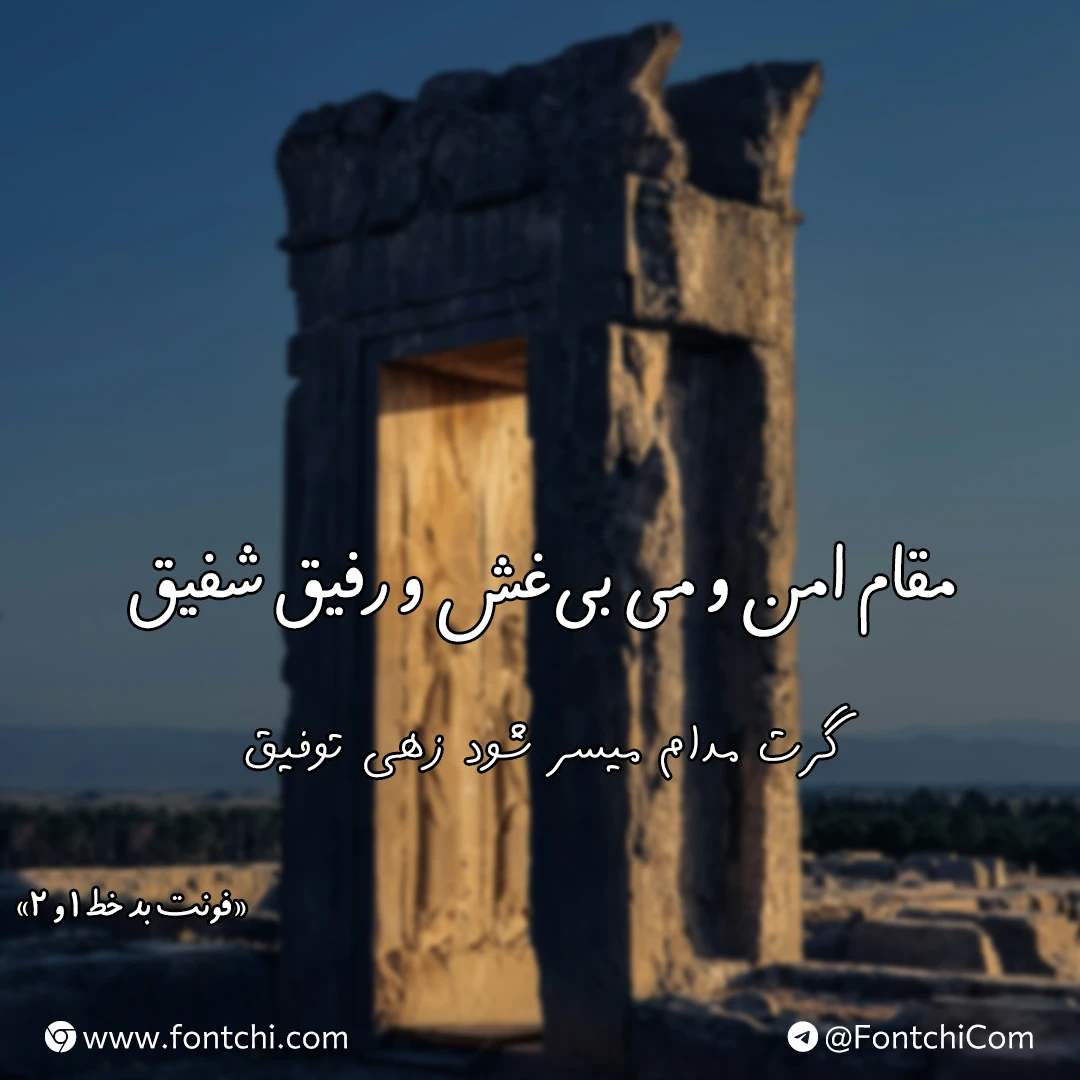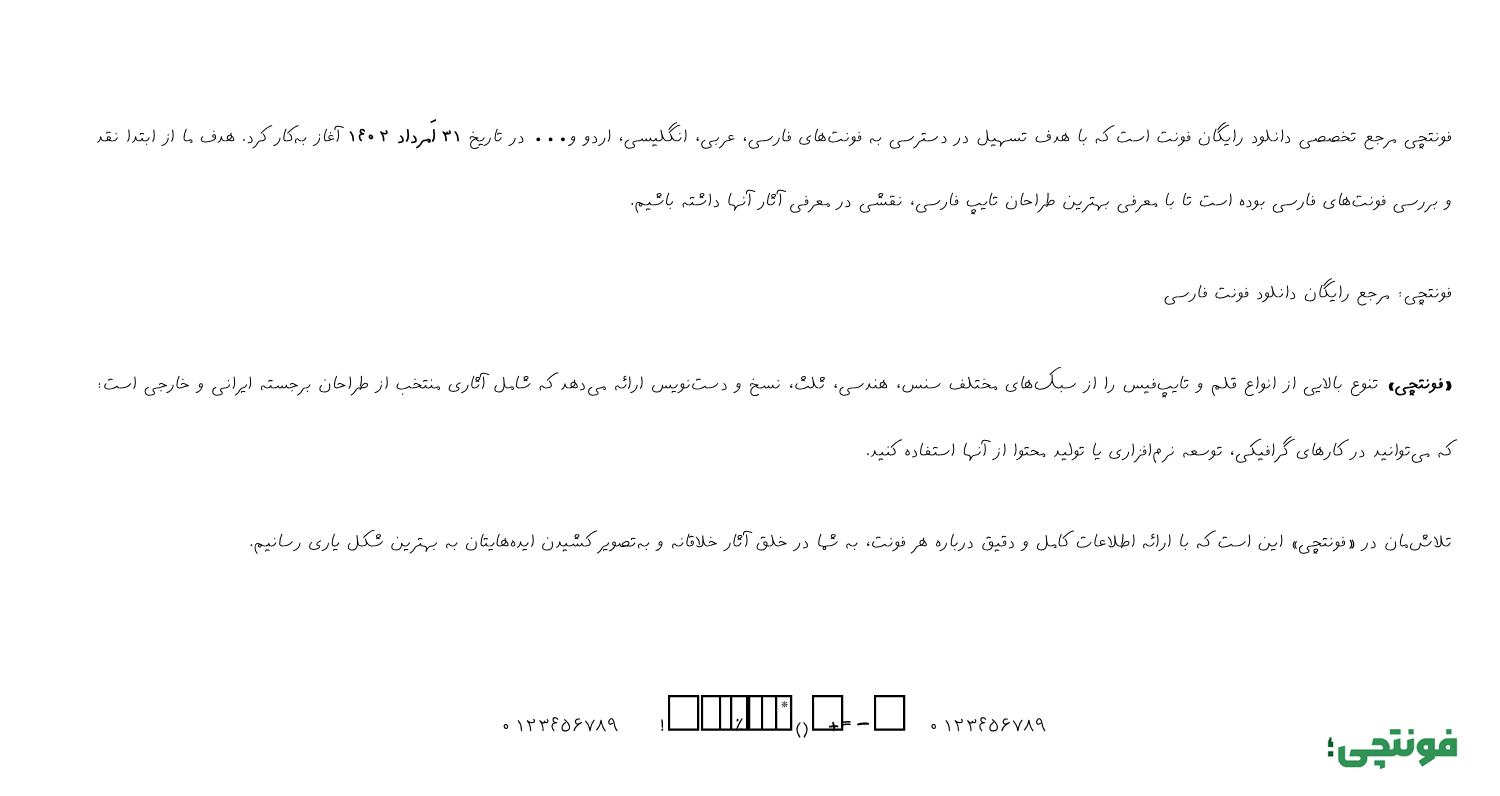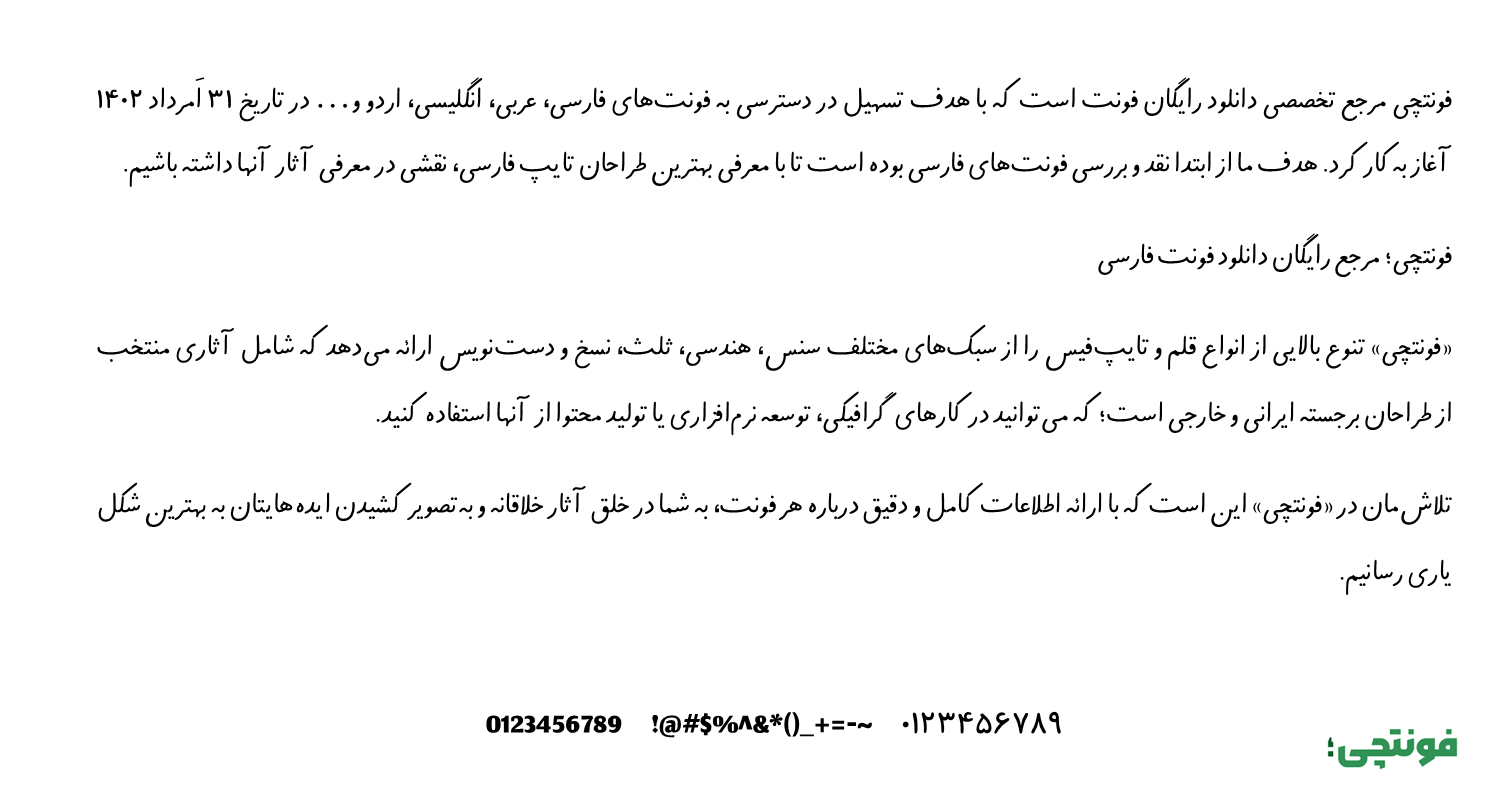
فونت بد خط (BadKhat) ۱ و ۲
| نام | بد خط ۱ و ۲ |
| نام نمایشی | A-bad Kh@t |
| طراح | امیرحسین صدقی |
فونت بد خط (به انگلیسی: BadKhat) به دلیل ساختار خاص و حس نوستالژیک خود جزو فونتهایی در دستهبندی دستنویس است که زیاد مورد توجه کاربران قرار گرفته است. این فونت در دو نسخه ۱ و ۲ توسط امیرحسین صدقی ارائه شده است.
در طراحی این فونت با الهام از دستخط طبیعی و خودکار، ظاهری صمیمی و غیررسمی به متون داده شده است. این فونت فارسی از زبانهای فارسی و عربی پشتیبانی نسبی دارد. در این مقاله، به نقد و بررسی ویژگیها، کاربردها، نقاط قوت و ضعف این دو فونت میپردازیم.
فونت بدخط یک فونت فارسی دستنویس است که با فرمت TTF عرضه شده و در نرمافزارهای مختلف مانند فتوشاپ، ورد، کورلدراو و حتی اپلیکیشنهای ویرایشگر موبایل مثل اینشات بهراحتی قابل استفاده است. این فونت در دو نسخهی بدخط ۱ و بدخط ۲ ارائه شده که هر کدام ویژگیهای خاص خود را دارند.
هدف اصلی این فونتها، ایجاد حس صمیمیت و نزدیکی در متون است، گویی که متن با دست و خودکار نوشته شده است. از اینرو، این فونتها برای پروژههای خلاقانه، کپشنهای اینستاگرام، طراحی پوستر، جلد کتاب، صفحات اجتماعی حاوی پستهای دلنوشته و حتی متون ادبی و رمان بسیار مناسب هستند.
این فونت فارسی از زبان عربی نیز پشتیبانی میکند. ولی باید به این نکته توجه داشته باشید که اعداد در این دو زبان استاندارد نیست و برای زبان عربی نیز از اعداد فارسی «۴۵۶» استفاده میشود.
اگر به دنبال فونتی رایگان، ساده و نوستالژیک برای پروژههای غیررسمی هستید، فونت بدخط ۱ انتخاب خوبی است. اما اگر پروژه شما نیاز به انعطاف بیشتر، خوانایی بهتر و ظاهری حرفهایتر دارد، فونت بدخط ۲ گزینه مناسبتری خواهد بود. با این حال، اگر به دنبال فونتی با گلیفهای پیشرفته یا وزنهای متنوعتر هستید، ممکن است لازم باشد به سراغ فونتهای حرفهایتر مانند ایران سنس یا نستعلیق بروید.
بررسی فونت بد خط ۱
فونت بدخط ۱ دارای طراحی ساده و مینیمال است که به دستخطهای روزمره و غیررسمی شباهت دارد. یادآور یادداشتهای دستنویس قدیمی است که حس صمیمیت را به مخاطب منتقل میکند. این فونت در سایزهای متوسط تا بزرگ خوانایی خوبی دارد، اما در سایزهای کوچک ممکن است کمی چالشبرانگیز باشد.
این فونت رایگان فارسی تنها در یک وزن (Regular) عرضه شده است. و از کاربردهای آن میتوان به طراحیهای غیررسمی، کپشنهای شبکههای اجتماعی، و متون کوتاه تبلیغاتی شاره کرد.
این نسخه از فونت دارای ظاهری نازک است که در متون کوچک بهخوبی خوانده نمیشود. با توجه به تنوع وزنی تکی مناسب پروژههای بزرگ نیست و از گلیفهای پیشرفته و خاص نیز پشتیبانی نمیکند.
بررسی فونت بد خط ۲
فونت بد خط ۲ نسبت به نسخه قبلی کمی حرفهایتر طراحی شده که دارای ظاهری بولد و ضخیم است. خوانایی مناسبتری هم دارد و در اندازههای بزرگ نیز ظاهر آن نمایشیتر میشود.
ازجمله کاربردهای آن میتوان برای طراحی پوستر، بنر، لوگوتایپ، و حتی متون ادبی مثل رمان و شعر اشاره کرد که با بهبود در اتصال گلیفها، سختار منظمتری ارائه میدهد.
از کپشنهای اینستاگرام گرفته تا طراحی حرفهای پوسترهای تبلیغاتی، میتوانید از این قلم استفاده کنید. این خانواده فونت با ایجاد تعادل بین ظاهر دستنویس و ساختار مدرن، برای مخاطبین جوان مناسب است.